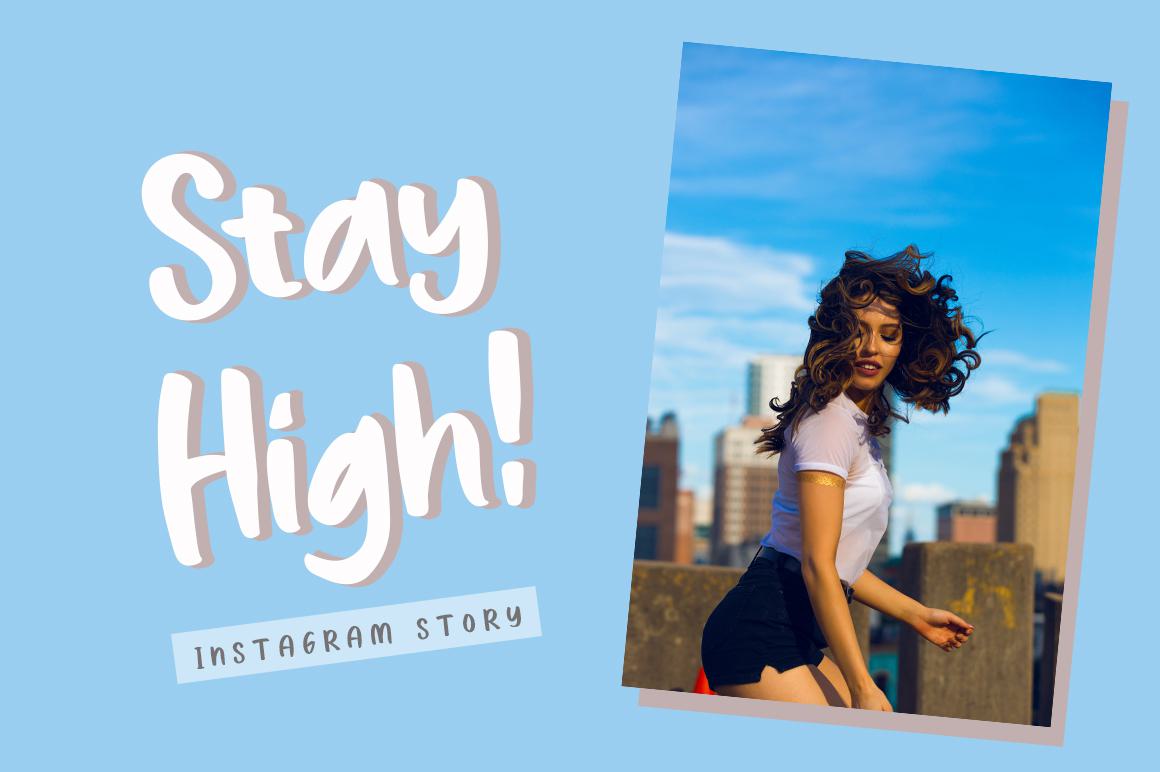
GrandRainbowScript是一款具有挤出式ADOWSTYLE的完美现代拼图字体。采用2层字体手写、复杂的流程。GrandRainbowScript为各种设计项目、签名、文具、徽标、排版引用、品牌、婚礼设计、社交媒体、,广告和产品设计。GrandRainbowScript是一款带有挤压式AdowStyle的完美现代拼图字体。采用2层字体手写、复杂的流程。GrandRainbowScript为各种设计项目、签名、文具、徽标、排版、品牌、婚礼设计、社交媒体、,广告和产品设计。